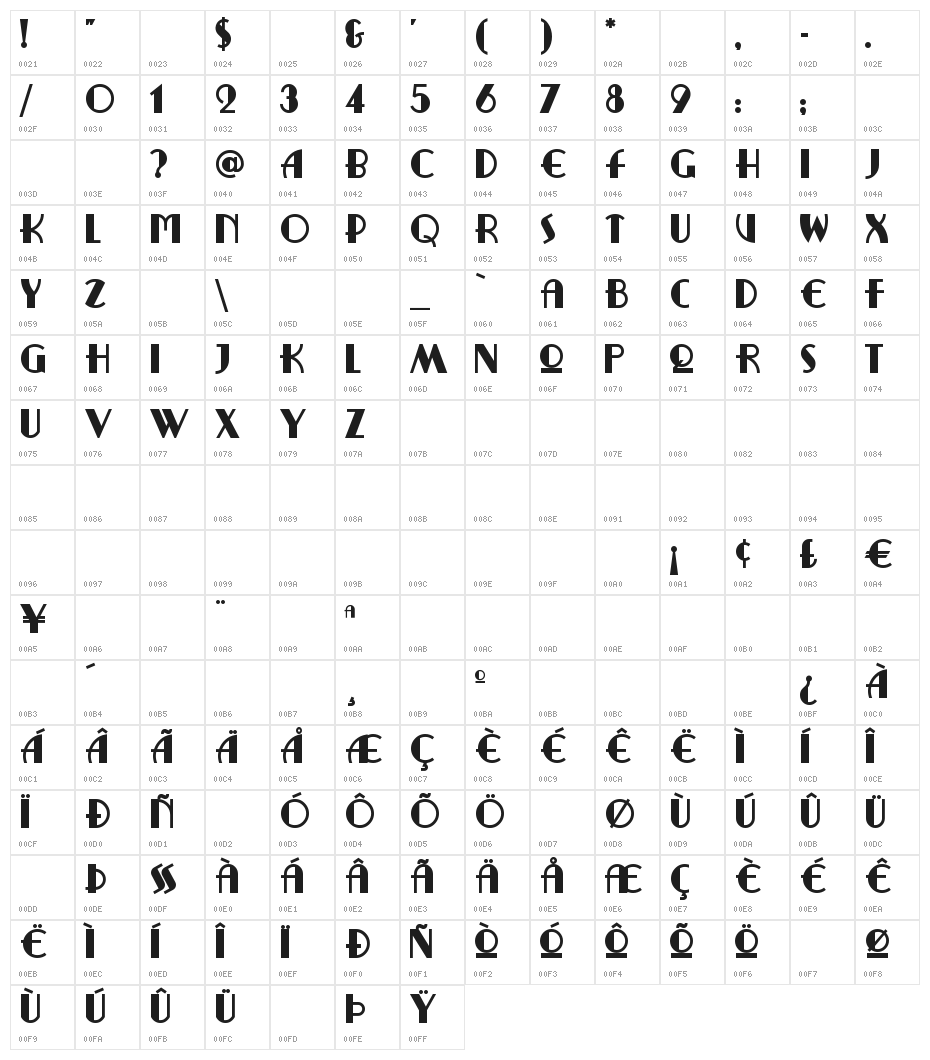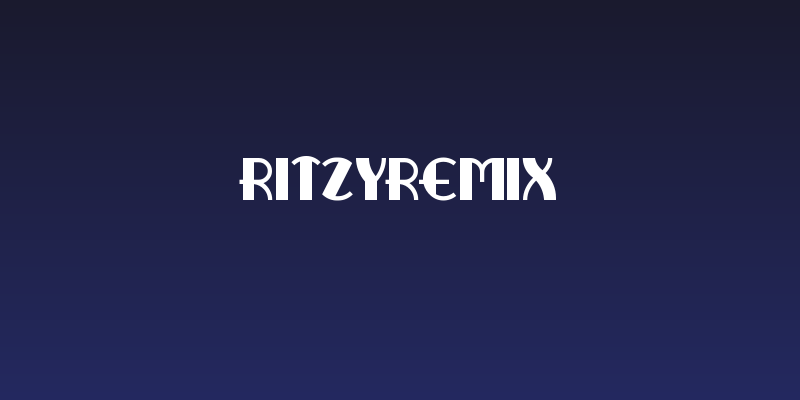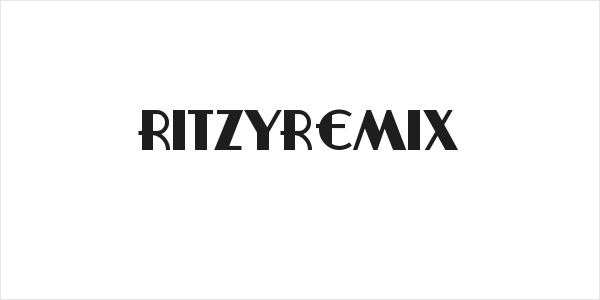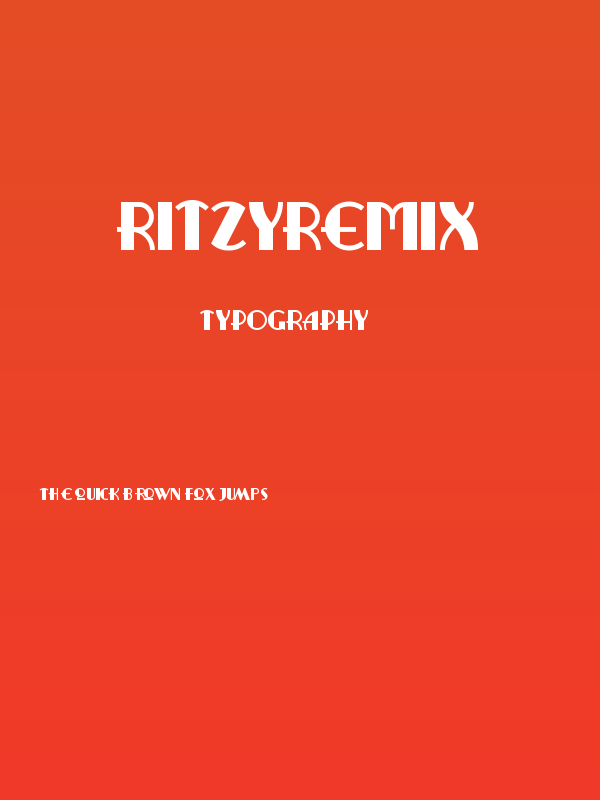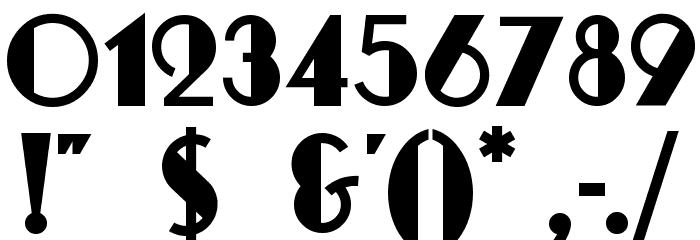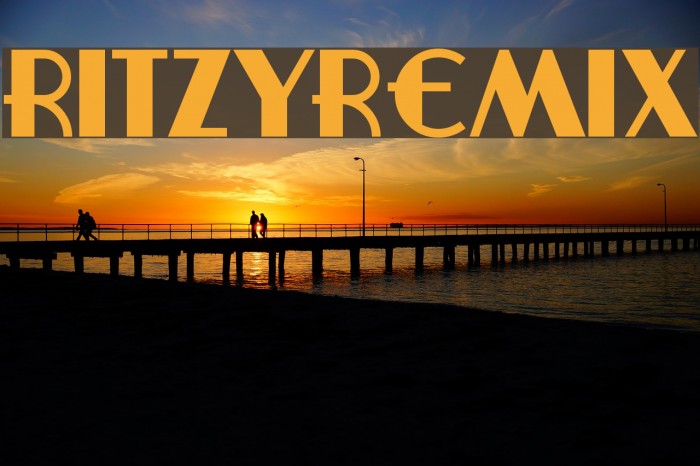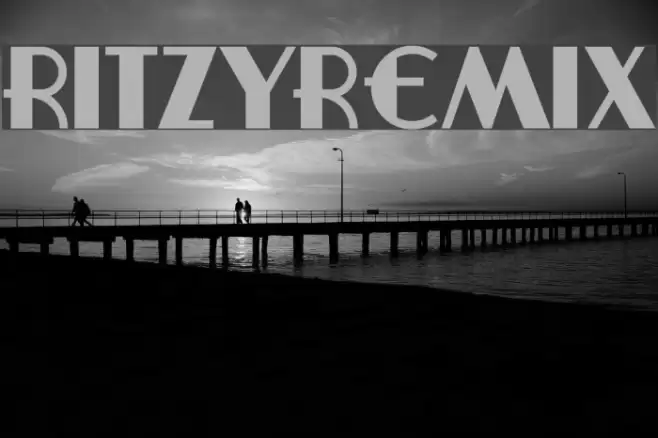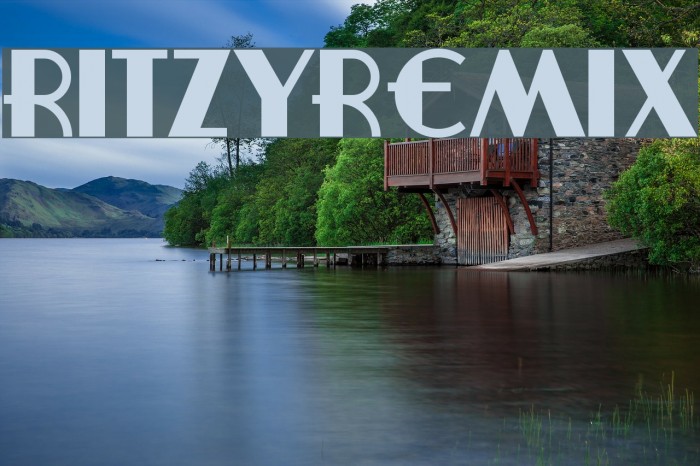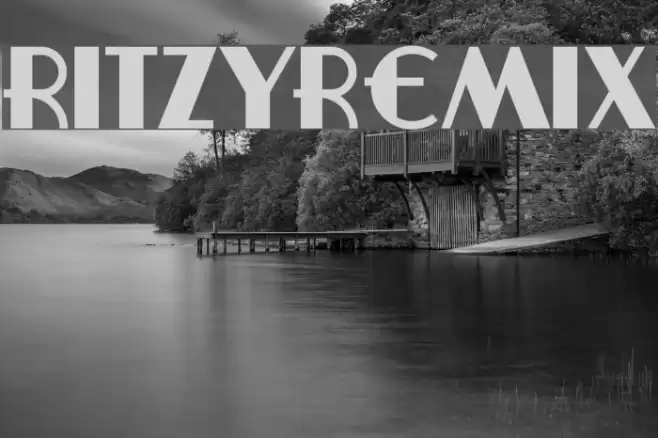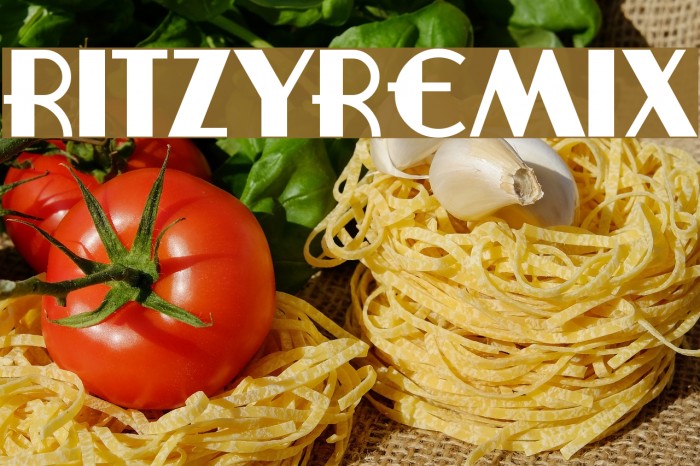
RitzyRemix Font
| Style général | Modern, Art Deco |
| Projets proposés | Ideal for branding, posters, headlines, and any design project requiring a bold, stylish statement. |